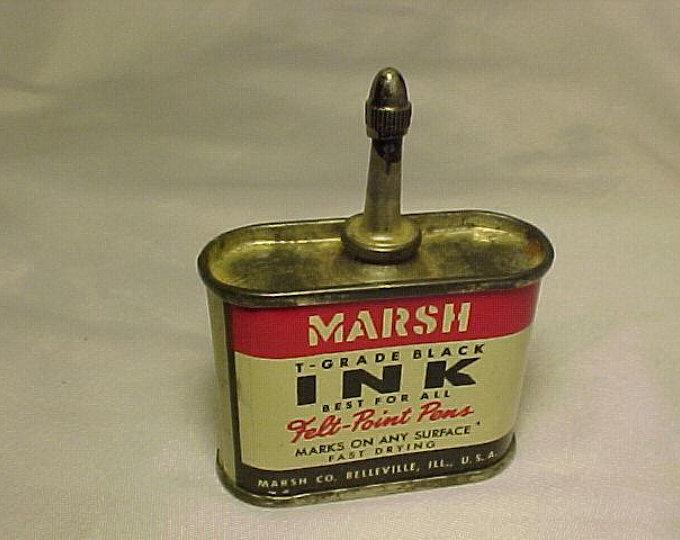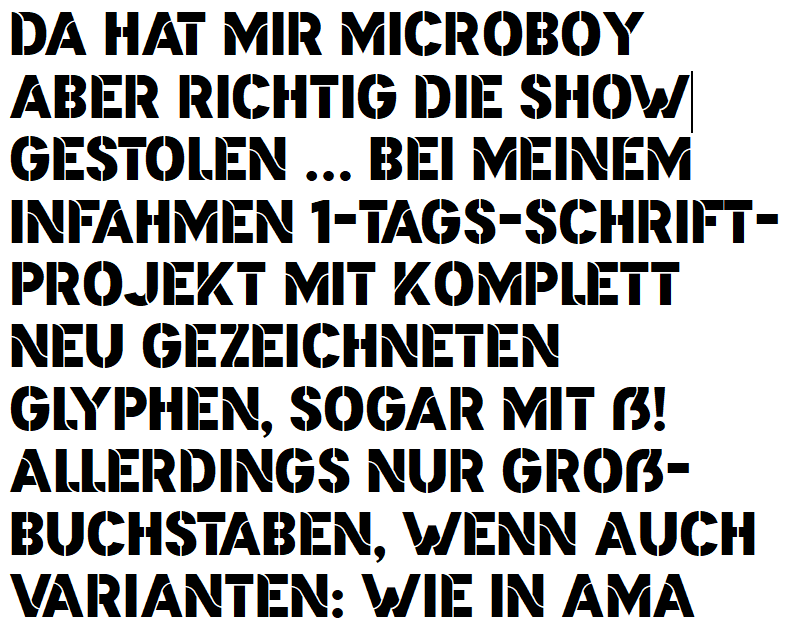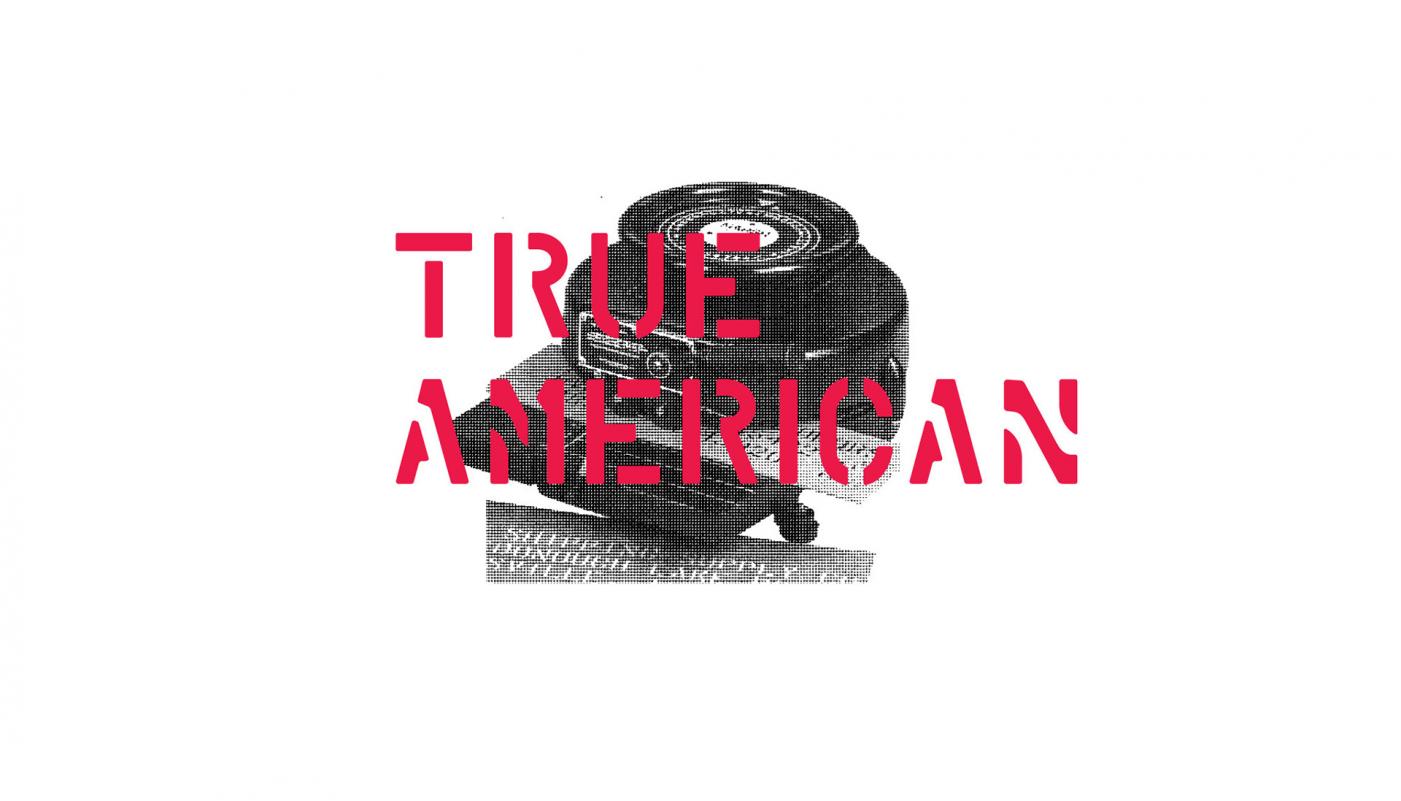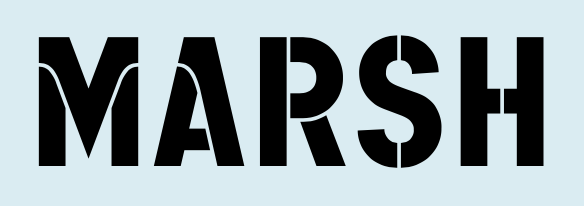
Suche Stencil-Font mit runden "Einschnitten"
ich bin vor Kurzem auf eine Stencil-Font gestoßen und versuche nun verzweifelt den Namen samt Foundry/Erwerbsort zu finden.
Vielleicht kennt hier jemand die Font, ich würde mich super freuen.
Da Marsh diese Buchstabenform schon in den 40er Jahren verwendet hat (so man diesem Vintage trauen darf), wird dem Logo keine Schriftart zugrunde liegen.
Das wäre echt schade. Hätte gedacht, dass es vllt eine eigene Font ist. Vermutlich wurde der Schriftzug dann nur über die Jahre angepasst. Vielleicht hat ja jemand noch einen Hinweis, aber trotzdem vielen Dank 🙂
Entstanden ist das aus einer Stencil-Schrift, also aus Schablonen, die z.B. zum Lackieren verwendet wurde. Das heutige Logo ist sicherlich gestaltet, nicht einfach aus einer bestehenden Schrift gesetzt.
Es gibt einen ähnlichen, der wohl näher am ursprünglichen Design dran ist:
Aber solche Logos können ja auch Grundlage eines Fonts werden... Mal sehen?
Aber solche Logos sund immer gut für neue Fonts zu bauen, mal sehen...
Wie wäre es mit der Cargo?
Oder hätte ich tatsächlich den Namen "Sund" nehmen sollen, und für die nebenbei entstandene ohne die Stencil-Stege dann "Belt"?